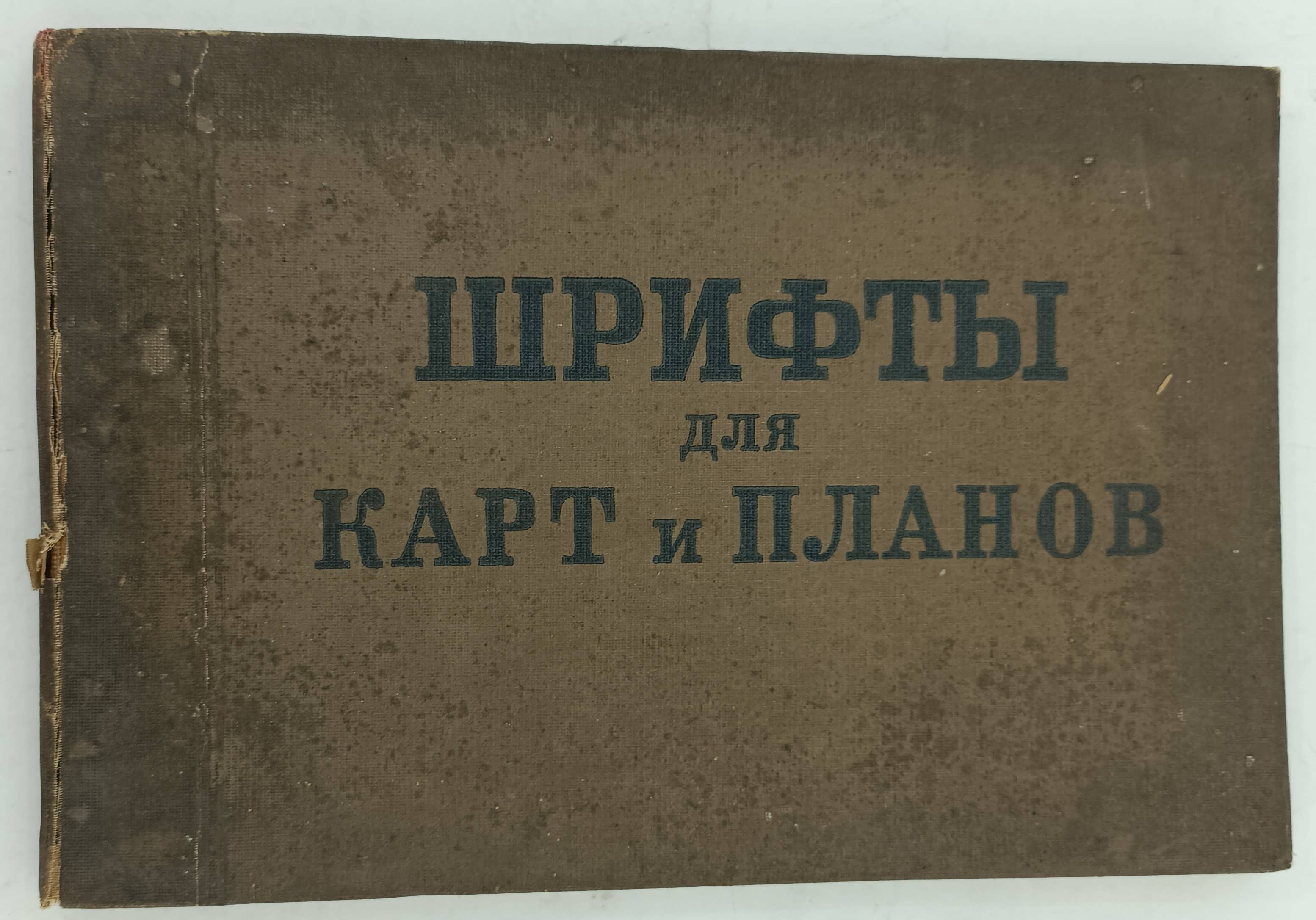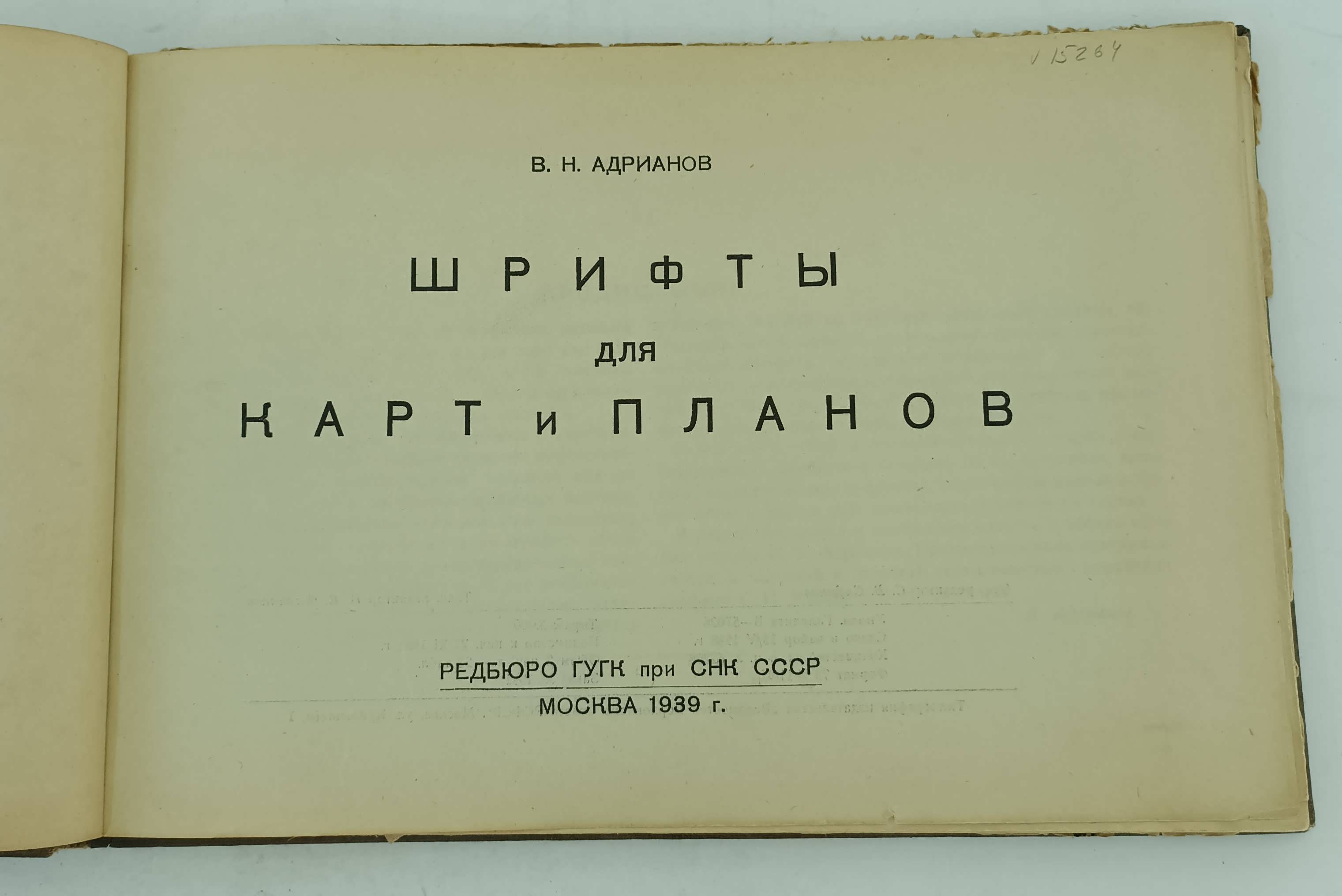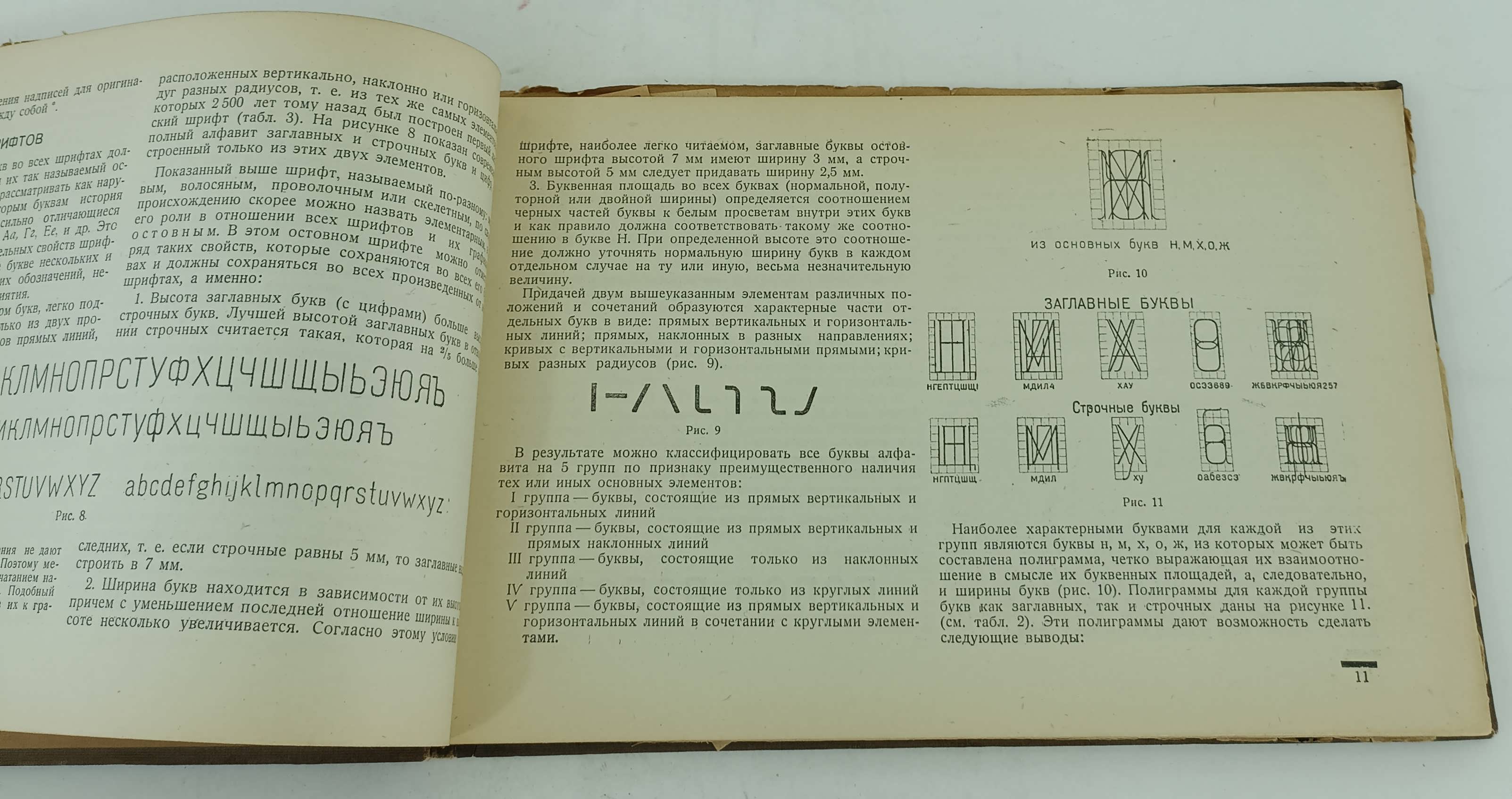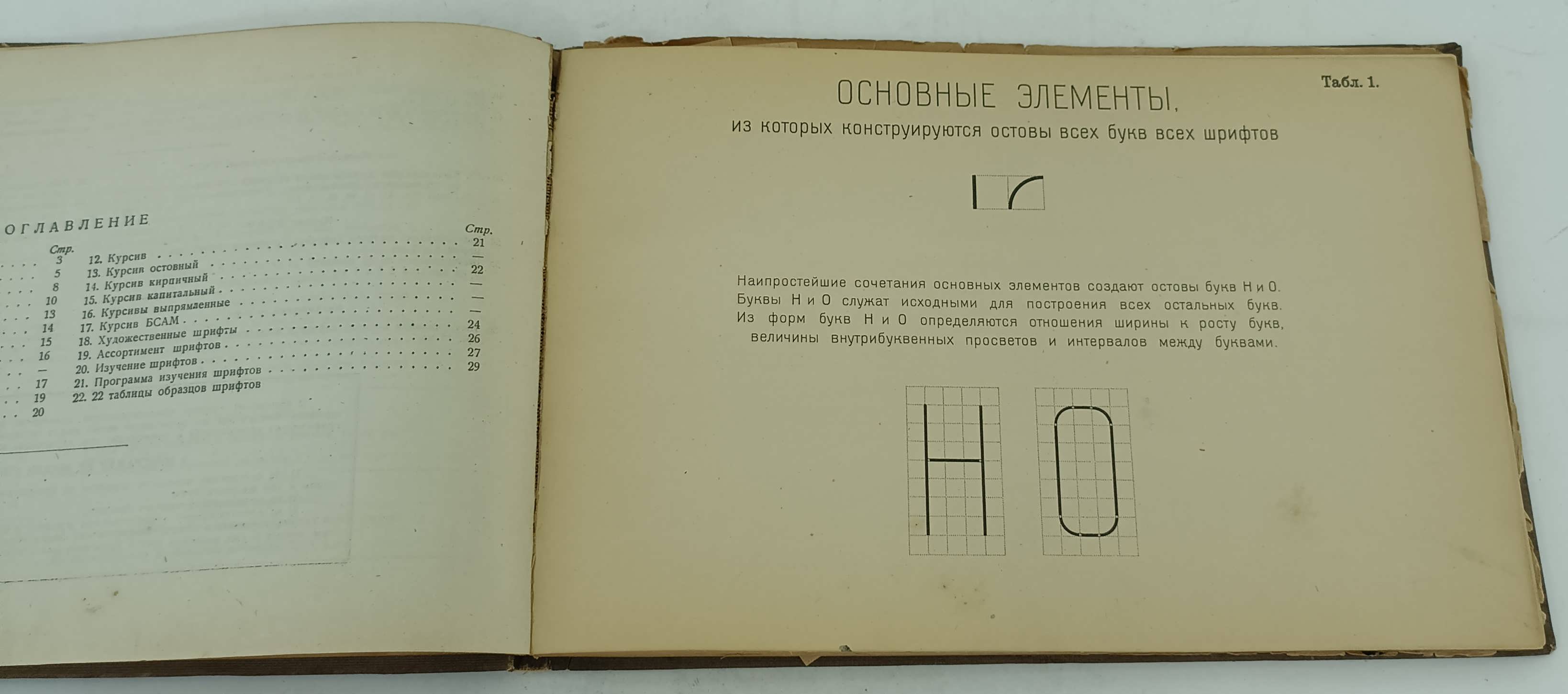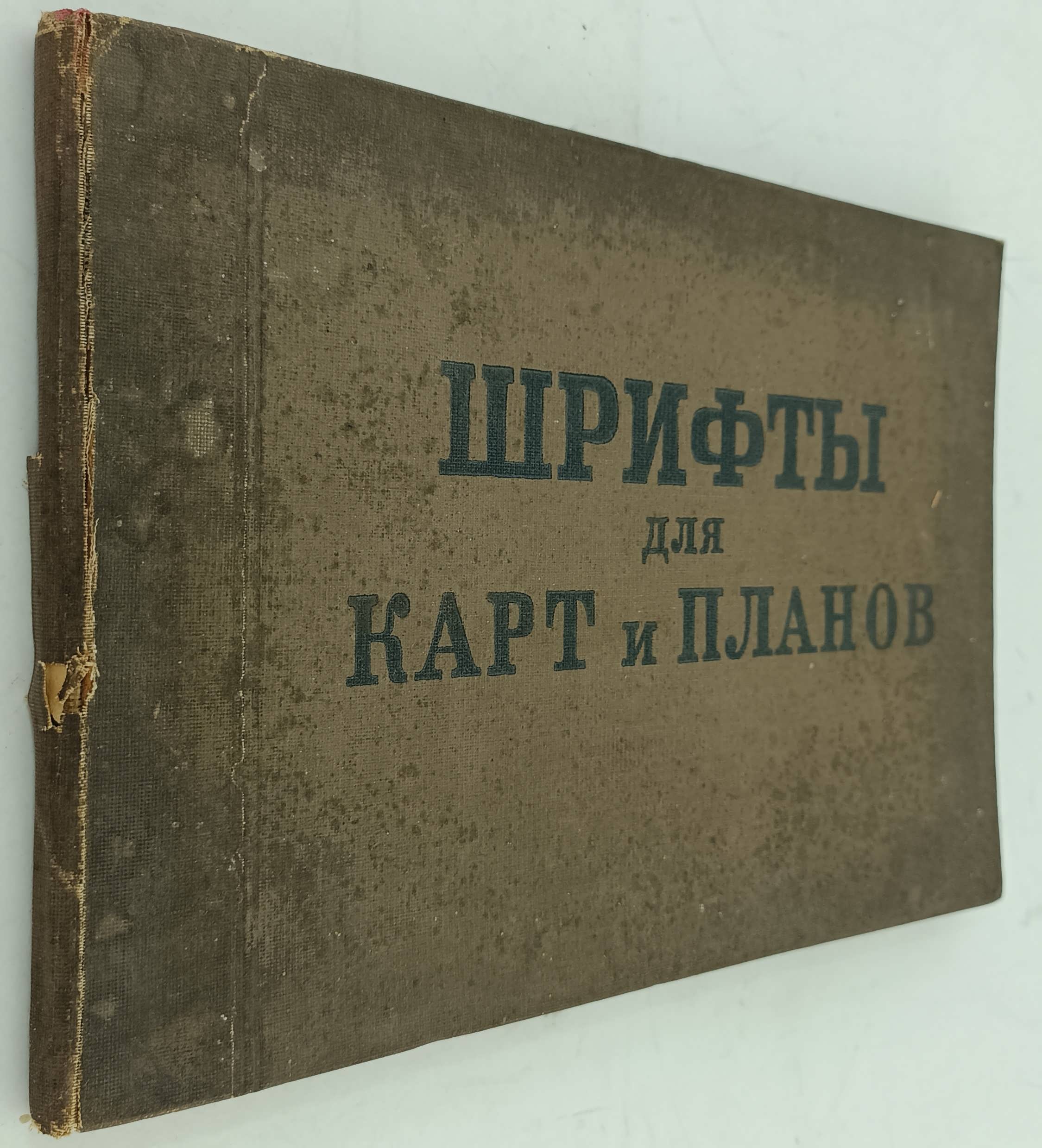
Шулейкин А.С., Федорченко М.В. и др. Шрифты для проектов, планов и карт.
Приведена методика исполнения надписей различными шрифтами при оформлении крупномасштабных проектов, планов и карт землеустройства, проектов архитектуры и планировки сельских населенных мест. Приведены образцы обыкновенных, картографических, архитектурных и художественных шрифтов, оформления заголовков проектов, планов и карт.